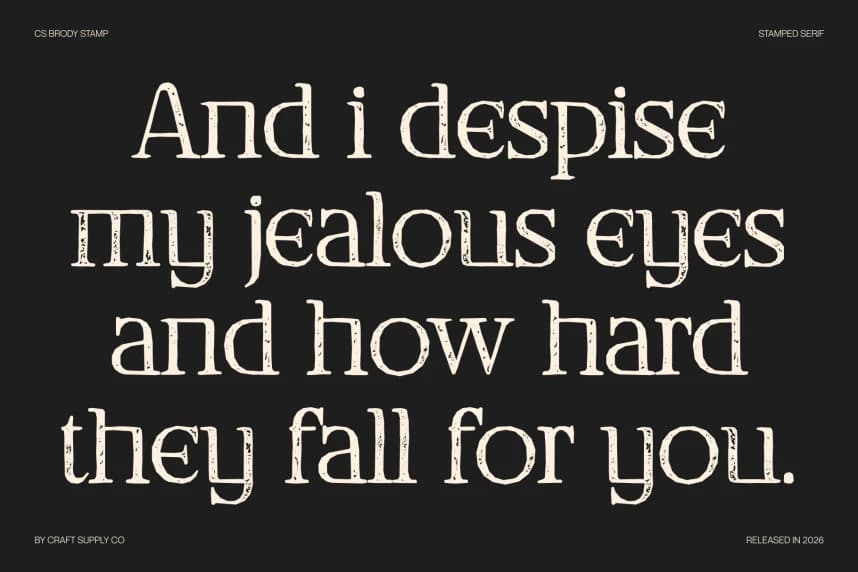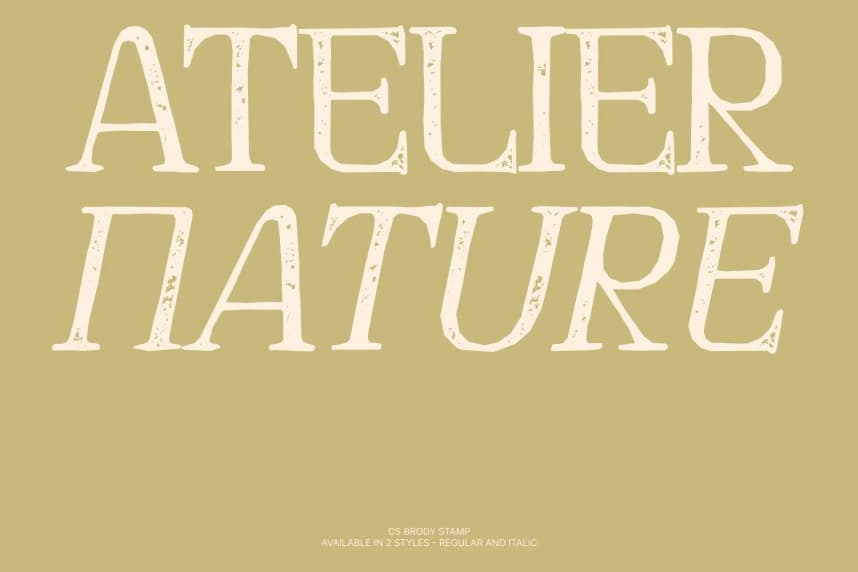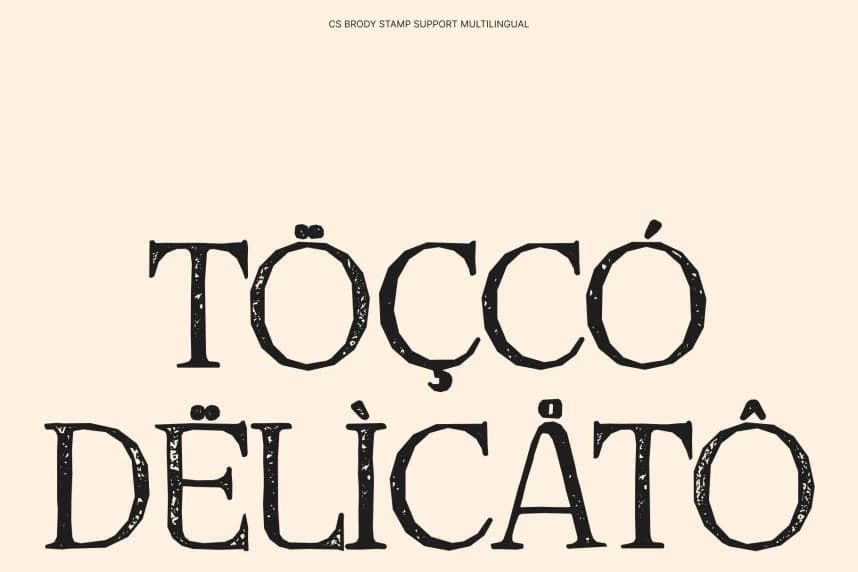
CS Brody Stamp Yazı Tipi
CS Brody Stamp Font – Klasik Serif Yazı Tipi, Dokulu Modern Zarafet ile Zamansız Zarafet Minimalist Sofistikasyonla Buluşuyor. Bu, klasik tipografinin çekiciliğini çağdaş tasarımın netliğiyle zarifçe harmanlayan modern bir serif yazı tipidir.
CS Brody Stamp Font – Klasik Serif, Dokulu Modern Zarafet Zamansız Zarafet Minimalist Sofistikasyonla Buluşuyor. Bu, klasik tipografinin çekiciliğini çağdaş tasarımın netliğiyle zarifçe harmanlayan modern bir serif fontudur.